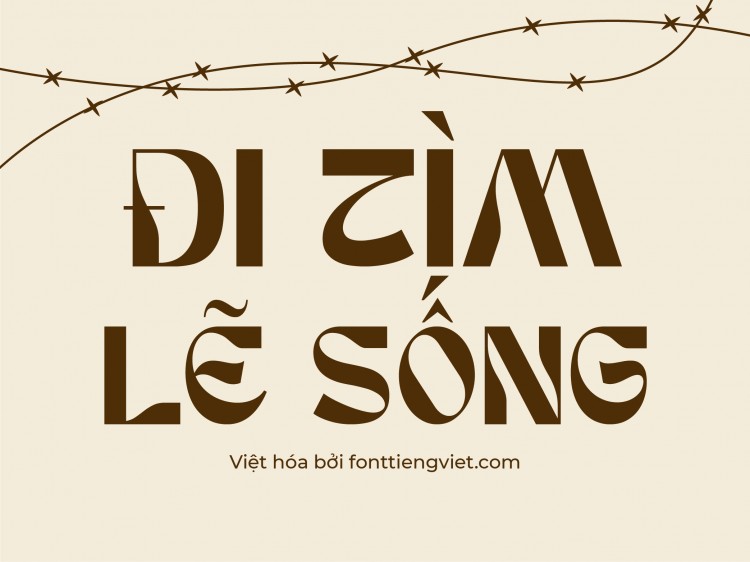
Font việt hóa 1FTV Nove
Giới thiệu về bộ Font việt hóa 1FTV Nove
Trong thế giới đồ họa hiện đại, việc lựa chọn Font Miễn Phí chất lượng đóng vai trò then chốt giúp sản phẩm trở nên thu hút. Font việt hóa 1FTV Nove là một phiên bản đặc biệt được tinh chỉnh kỹ lưỡng để phù hợp với bảng mã tiếng Việt. Đây là bộ phông chữ thuộc trường phái không chân (sans-serif) mang hơi hướng hiện đại, thanh lịch và cực kỳ tối giản. Với đường nét sắc sảo, 1FTV Nove giúp các bạn học sinh và giáo viên dễ dàng tạo ra những slide thuyết trình hoặc tài liệu học tập đẹp mắt, chuyên nghiệp mà không lo lỗi font khi gõ dấu.
Ưu điểm nổi bật của Font việt hóa 1FTV Nove
Thiết kế hiện đại và tính ứng dụng cao
Đặc điểm lớn nhất của Font việt hóa 1FTV Nove chính là sự cân bằng giữa các ký tự. Khoảng cách chữ được thiết kế thoáng đãng, giúp người đọc không bị mỏi mắt khi theo dõi các văn bản dài. Bộ font này rất đa năng, từ thiết kế bìa sách, poster sự kiện trường học cho đến các ấn phẩm truyền thông trên mạng xã hội. Sự tinh tế trong từng nét chữ giúp truyền tải thông điệp một cách rõ ràng và trực diện nhất.
Hỗ trợ tiếng Việt hoàn chỉnh
Khác với các phiên bản gốc thường gặp lỗi hiển thị dấu câu, Font việt hóa 1FTV Nove đã được tối ưu hóa toàn bộ hệ thống dấu tiếng Việt. Điều này giúp các nhà thiết kế tại Việt Nam tiết kiệm thời gian chỉnh sửa thủ công. Bạn có thể tự tin sử dụng bộ font này trên nhiều phần mềm thiết kế phổ biến như Photoshop, Canva hay thậm chí là Microsoft Word để phục vụ nhu cầu học tập và giảng dạy hàng ngày.